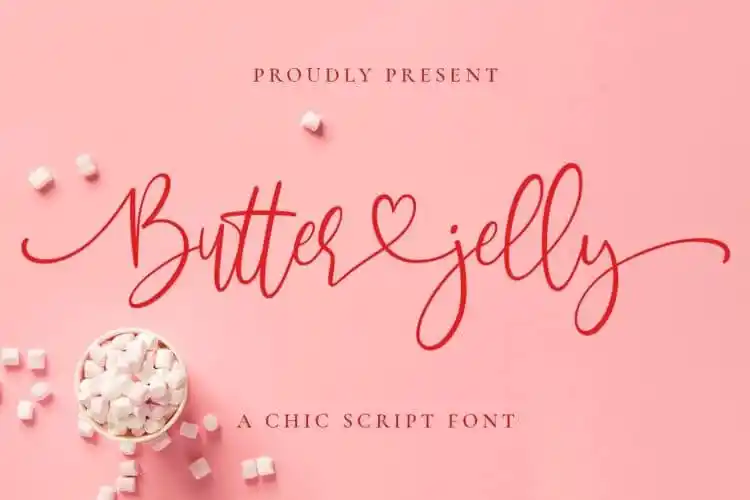
Butter Jelly Script Font – Download Grátis
A Butter Jelly Script Font é uma peça de arte tipográfica que se sobressai entre as demais por sua autenticidade natural. Feita com delicada escrita à mão, você pode criar letras manuscritas perfeitamente ao simplesmente digitar no teclado. Com linhas marcadas e finas, o fluxo desses elementos cria um trabalho de arte autêntico que exala harmonia e graça. A fonte é repleta de corações, símbolos e letras de outros tipos. O design contém traços muito acentuados e uma linha base ondulante suave, o que lhe dá um toque irresistivelmente charmoso. Ideal para logos, papelaria da festa, cartas, designs de presentes, fotografias, marcadores d’água, embalagens de produtos e citações escritas à mão – a Butter Jelly Script é uma escolha inspiradora para qualquer projeto que exija um toque romântico e elegante.